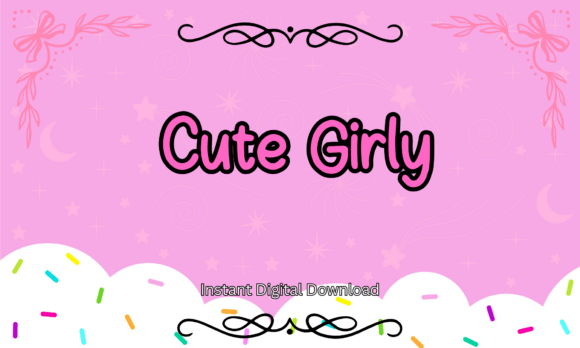
Cute Girly
適切なデザイン要素を見つけるのは難しい場合がありますが、Cute Girlyは作品を即座に引き立てる優れたコレクションを提供します。
POD(オンデマンド印刷)製品、結婚式の招待状、またはソーシャルメディアのグラフィックを作成している場合でも、Cute Girlyは理想的です。